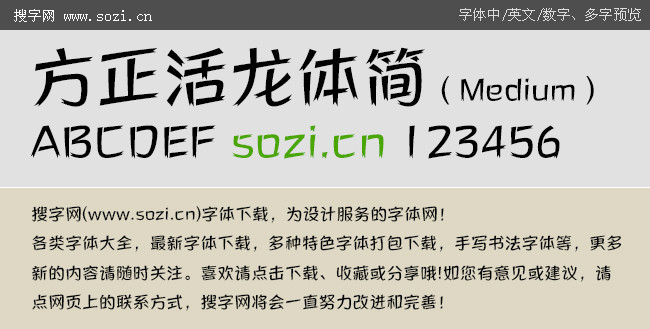
方正活龍體簡Medium
搜字網提供一款方正活龍體簡中文字體下載,方正活龍體簡是方正字庫全新開發(fā)的一款非常實用的字體,該字體特點是橫、直劃粗細平均,所有筆劃頭部斜直而末端開了叉口,而且點,撇,捺,抅等都是弧形,沒有垂直平行線的,橫劃重心向右上方斜上,讓它活一些,有動感和速度,像一條龍在天空飛舞,可以應用于網頁設計、包裝設計、海報設計等廣告設計場合使用。